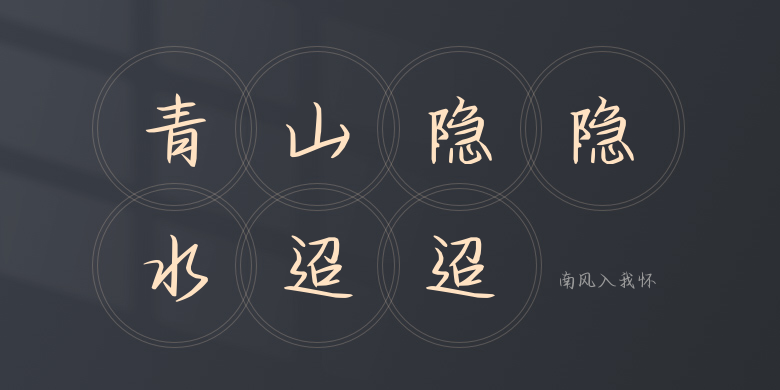
南风入我怀
南风入我怀,这款字体结构工整、笔画清晰,兼顾美观与易读性,适用于标题、正文、海报、包装、LOGO 等多种场景。字形优雅稳定,风格百搭耐看,适配日常排版与创意设计,让文字呈现更舒适、更具质感。南风入我怀一笔一画,皆是细节,以均衡的比例、流畅的线条打造舒适视觉体验,字形端正大气,风格简约现代。无论是商业设计、品牌宣传还是日常排版,都能轻松驾驭,让文字更有格调与力量。南风入我怀字体下载。